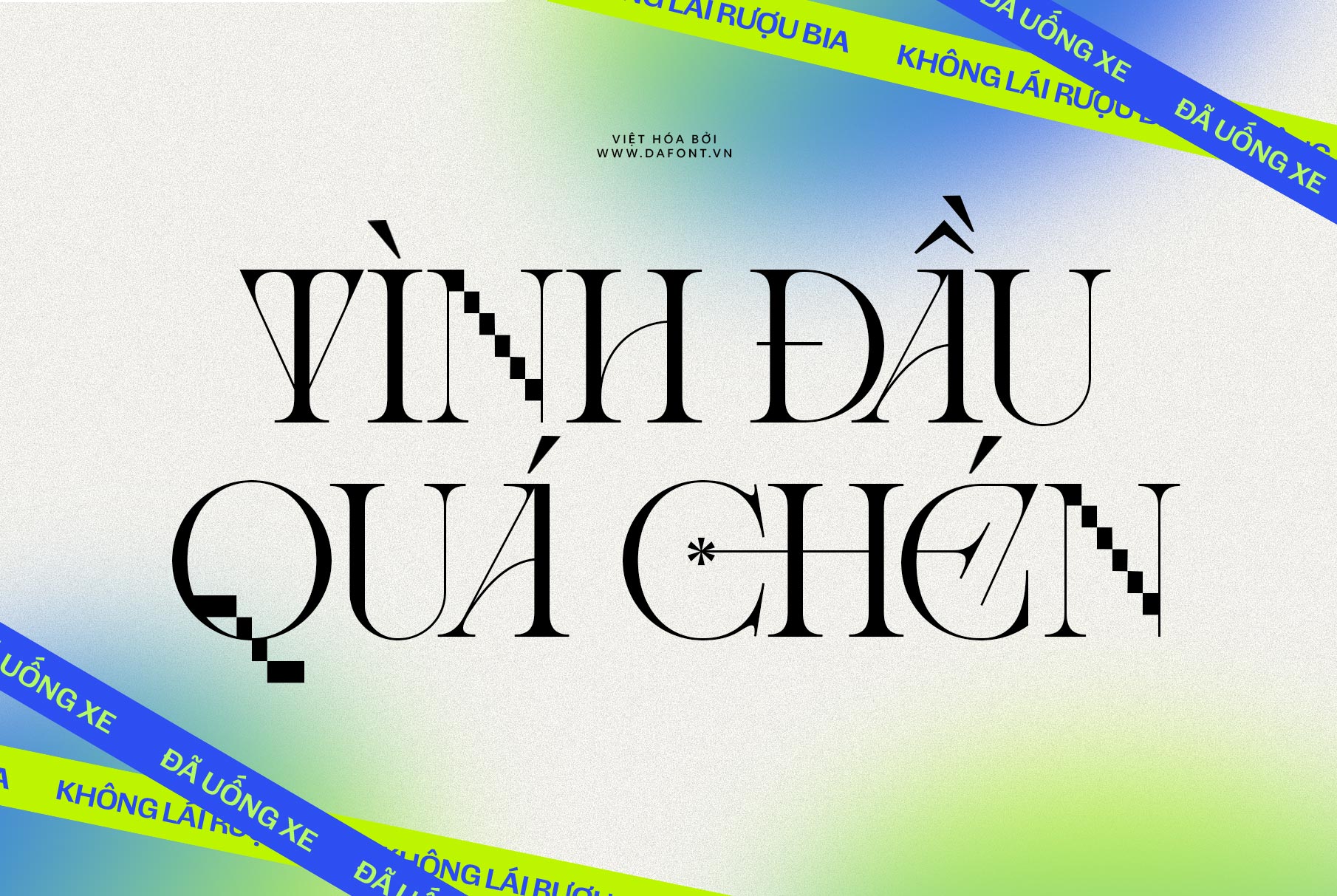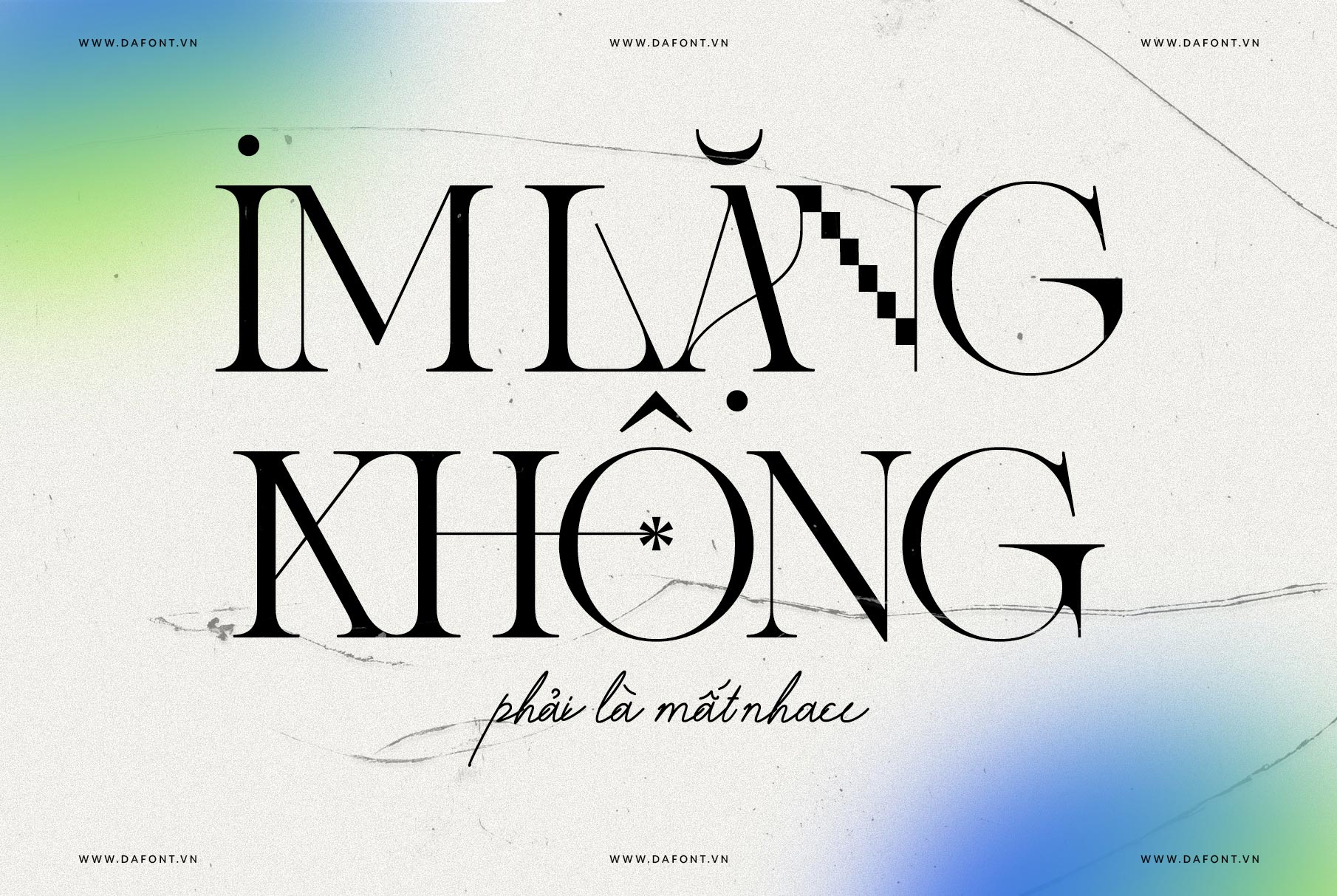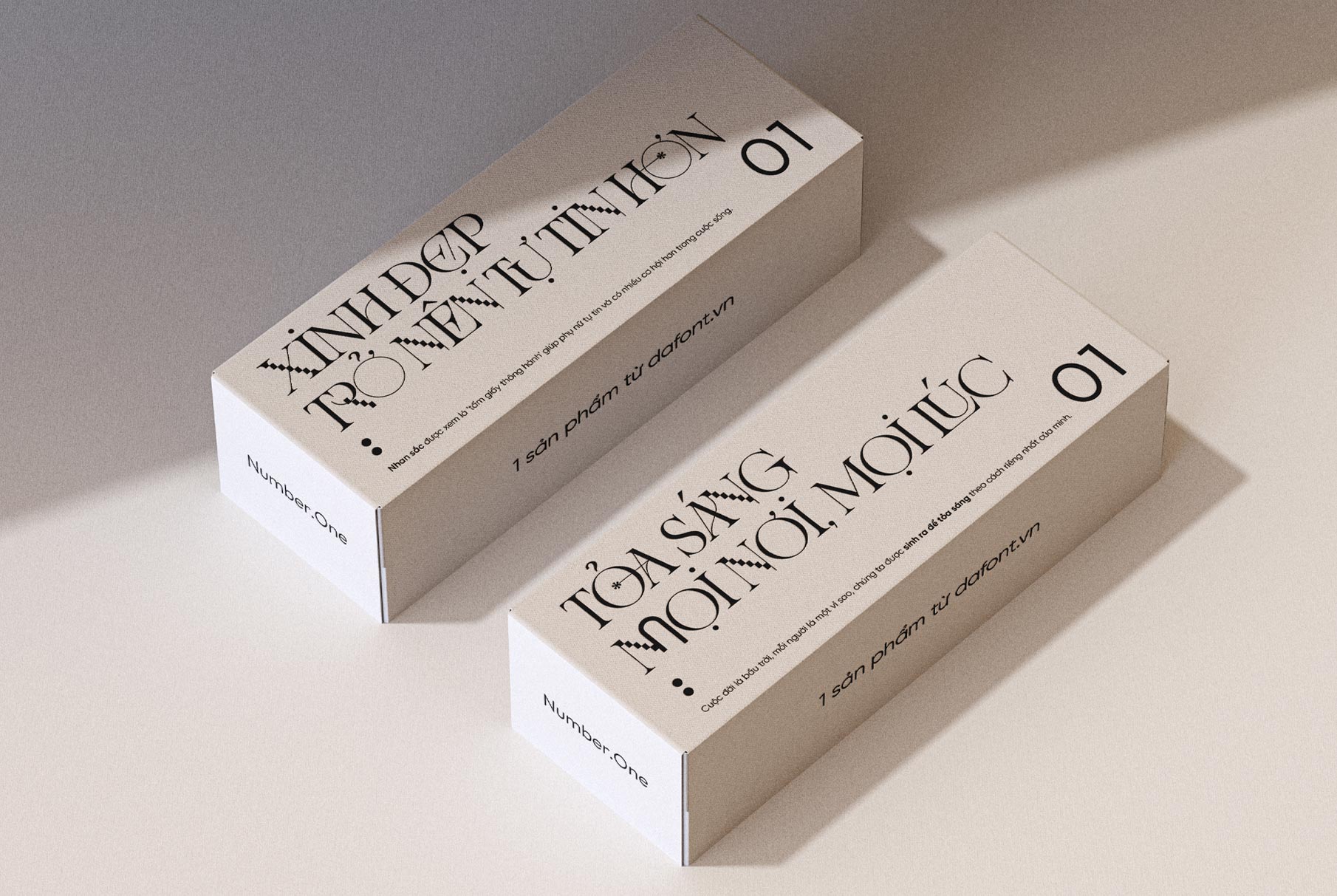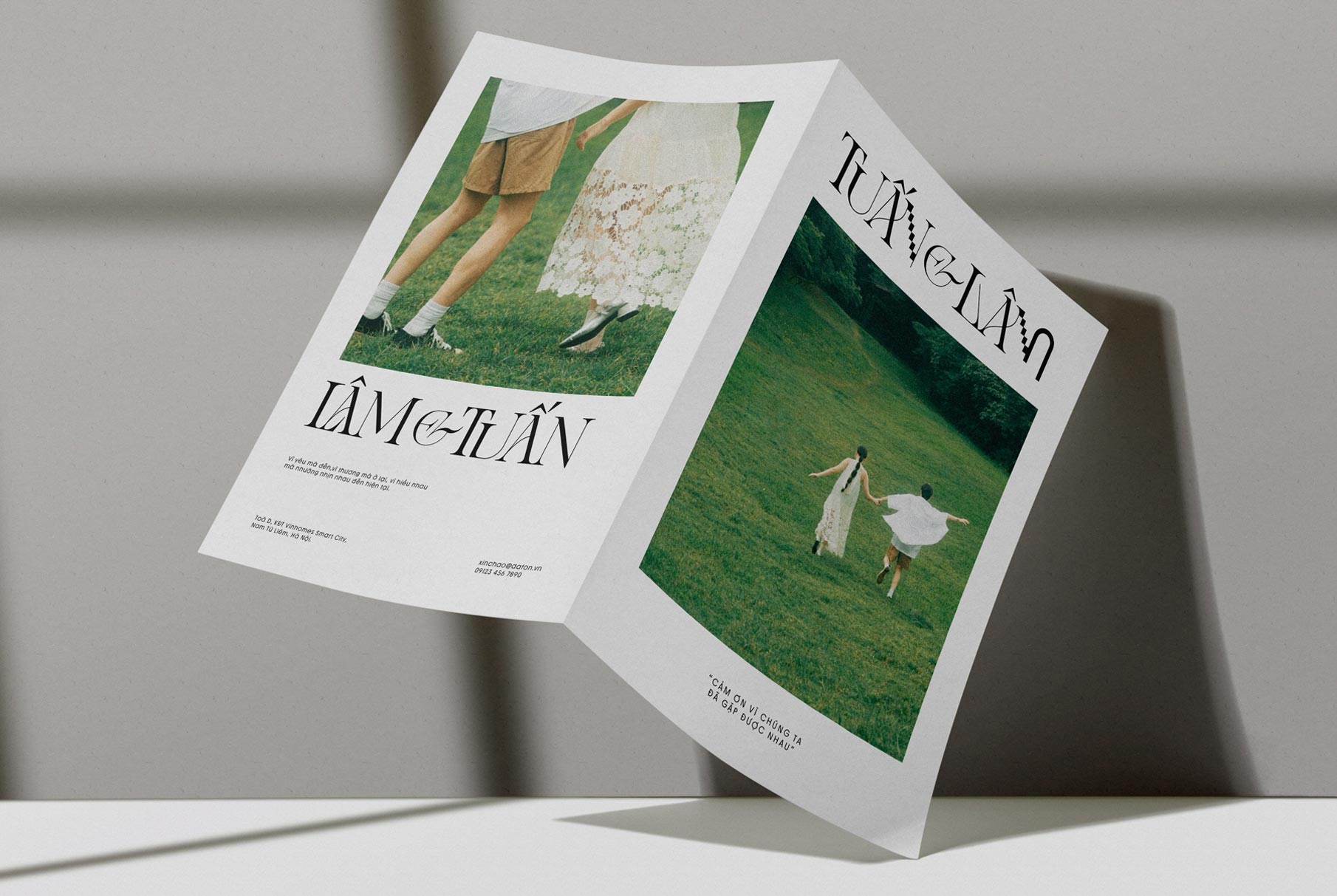
Trong thế giới typography đang ngày càng đa dạng, DFVN Amelie Fierce đã xuất hiện như một làn gó nào mới, kết hợp hoàn hảo giữa sự độc đáo và phong cách đột phá hiện đại. Font chữ này không chỉ là một công cụ thiết kế, mà còn là nguồn cảm hứng cho những ai muốn tạo nên sự khác biệt.
DFVN Amelie Fierce tạo điểm nhấn với hơn 280 ligature độc đáo và các chi tiết pixel đầy sáng tạo. Hãy cùng khám phá vì sao font chữ này là sự lựa chọn hoàn hảo cho thiết kế của bạn.
Đặc điểm nổi bật DFVN Amelie Fierce
Amelie Fierce là một font chữ ấn tượng, kết hợp giữa sự thanh lịch cổ điển và phong cách hiện đại táo bạo. Dưới đây là những đặc điểm nổi bật làm nên sức hút của font chữ này:
- Hơn 280 chữ ghép độc đáo: Amelie Fierce mang lại sự sáng tạo không giới hạn với hơn 280 ligature độc nhất. Từ những cặp chữ thông thường, bạn có thể biến hóa thành những chi tiết đầy cuốn hút, giúp tăng sự nổi bật cho thiết kế.
- Phong cách pixel đột phá: Sự kết hợp các đường nét pixel trong Amelie Fierce mang lại vẻ độc đáo và đầy táo bạo. Đây là yếu tố hoàn hảo cho những thiết kế muốn tạo ra một chút thú vị.
- Vẻ đẹp của sự hiện đại: Amelie Fierce được thiết kế dành cho các dự án biên tập, bố cục thời trang và thương hiệu cao cấp. Nét chữ tương phản cao kèm theo các chi tiết tỉ mỹ tạo nên vẻ sang trọng, tinh tế.
- Dễ dàng kết hợp với các font khác: Font chữ này hoạt động tốt khi kết hợp với các font sans-serif đơn giản để tạo sự tương phản.
DFVN Amelie Fierce phù hợp cho những dự án nào?
Font chữ này mang phong cách hiện đại, sang trọng, đi kèm các ký tự thay thế và các chữ ghép độc đáo, giúp tạo điểm nhấn ấn tượng có thể phù hợp cho nhiều dự án thiết kế khác nhau.
- Xây dựng thương hiệu: Nâng tầm logo, bao bì và chiến dịch với các đường nét sắc sảo.
- Tiêu đề nổi bật: Tạo điểm nhấn với các tiêu đề đầy sức hút.
- Thiết kế xu hướng: Mang phong cách hiện đại, tiên phong vào website, đồ họa mạng xã hội và thời trang.
- Poster & Thiệp mời: Tạo các poster và thiệp mời ấn tượng, kết hợp sự thanh lịch với chút nổi loạn bất ngờ.
- Bìa sách, tạp chí: Thiết kế bìa sách hoặc tạp chí bắt mắt, gợi lên nội dung hấp dẫn.
- Bao bì sản phẩm độc đáo: Làm nổi bật sản phẩm của bạn với bao bì toát lên sự tinh tế và một chút độc đáo.
DFVN Amelie Fierce không chỉ là một font chữ, mà còn là một công cụ sáng tạo mạnh mẽ giúp bạn thể hiện cá tính và phong cách riêng trong từng thiết kế. Hãy khám phá và sử dụng ngay hôm nay để tạo nên những tác phẩm đầy cảm hứng!
Đặc biệt, DFVN Amelie Fierce đã thiết kế mới và việt hóa tất cả các chữ ghép với hơn 1.000 chữ ghép độc đáo, bạn có thể dễ dàng sử dụng bằng tính năng Opentype. Với những chữ ghép vô cùng bắt mắt này sẽ giúp thiết kế của bạn trở nên tỏa sáng và thú vị hơn rất nhiều.